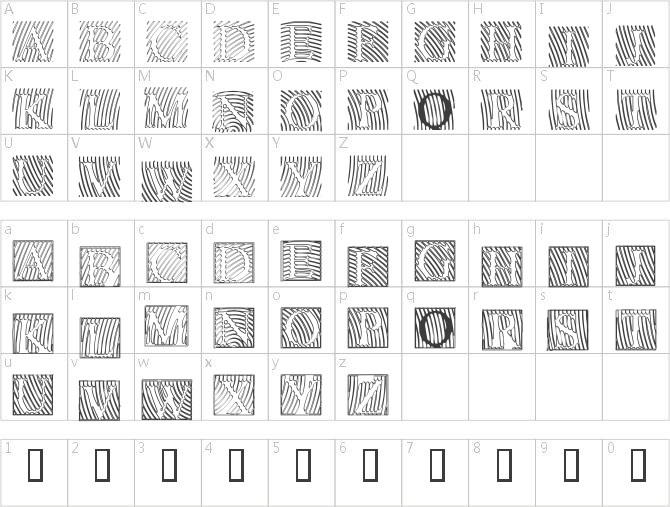
LowEngravedCapsHollow
LowEngravedCapsHollow介紹
LowEngravedCapsHollow字體字庫是一款讓人賞心悅目、百看不厭的英文字體,適合各類廣告和產品包裝設計應用,字體大小0.1MB,格式為ttf字體,上傳用戶是瀨子,作者/版權方為未知
LowEngravedCapsHollow效果圖